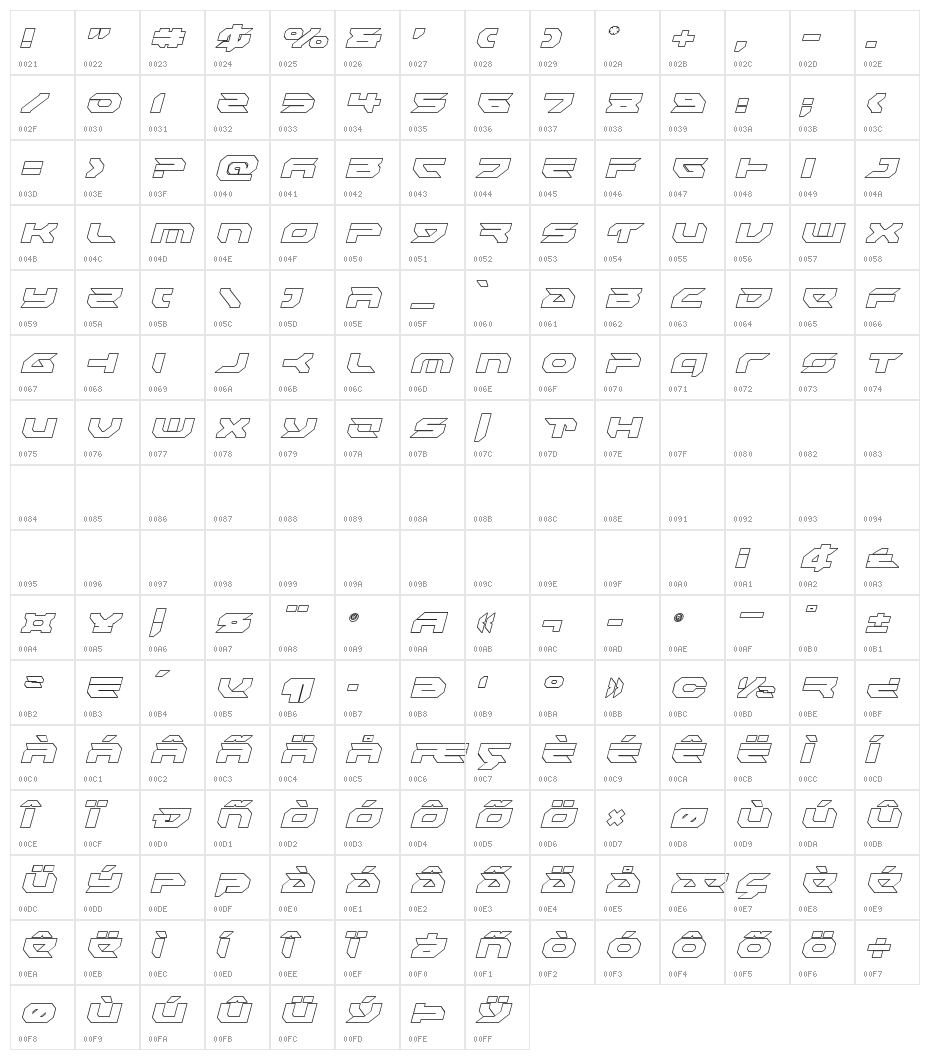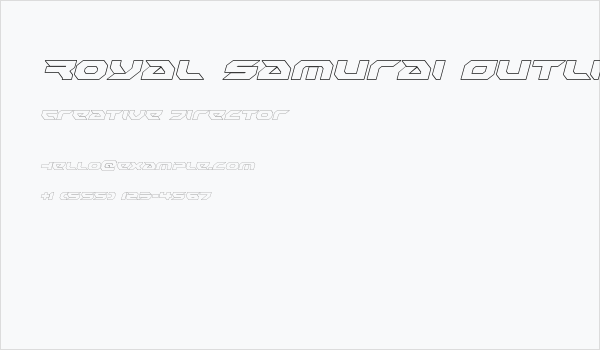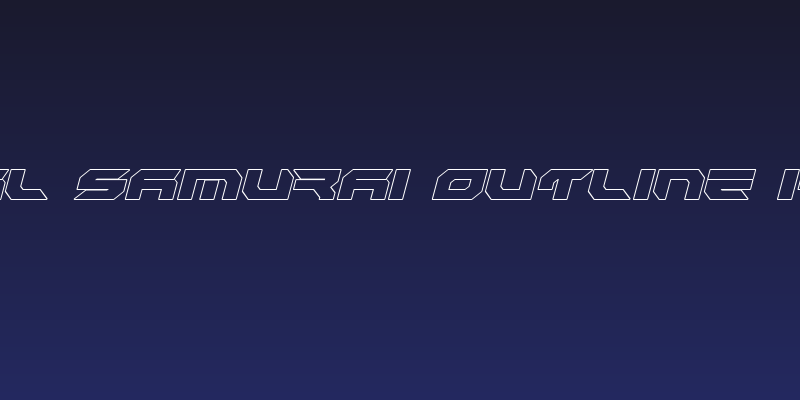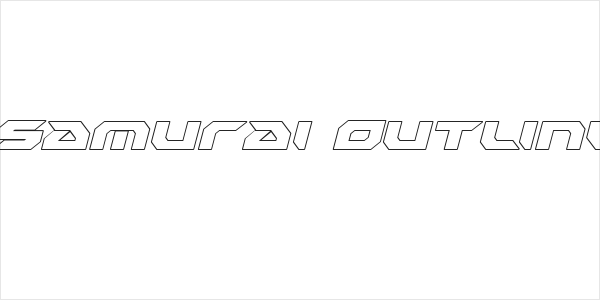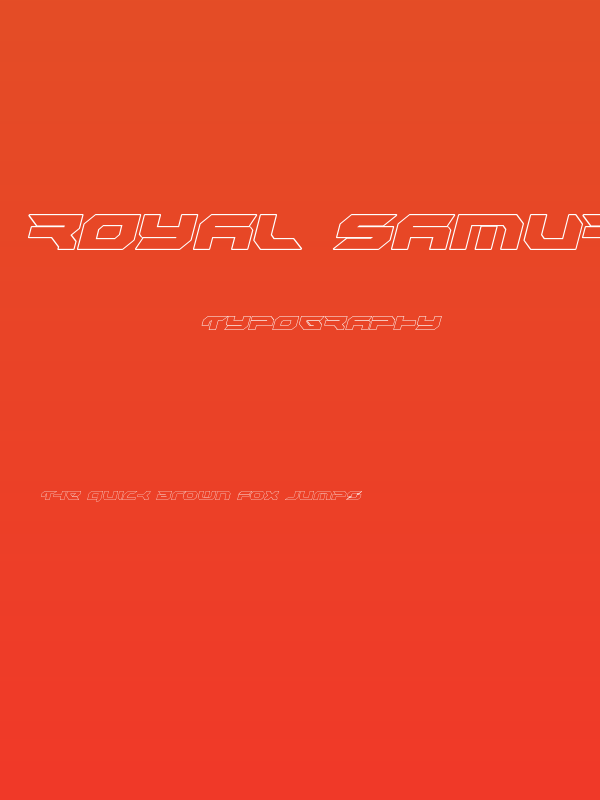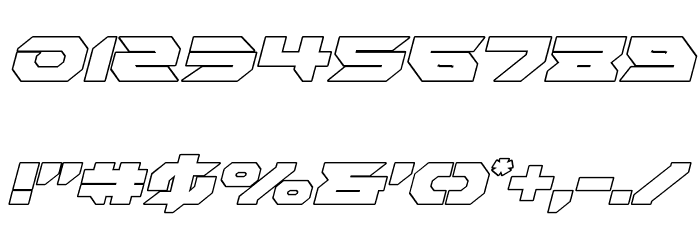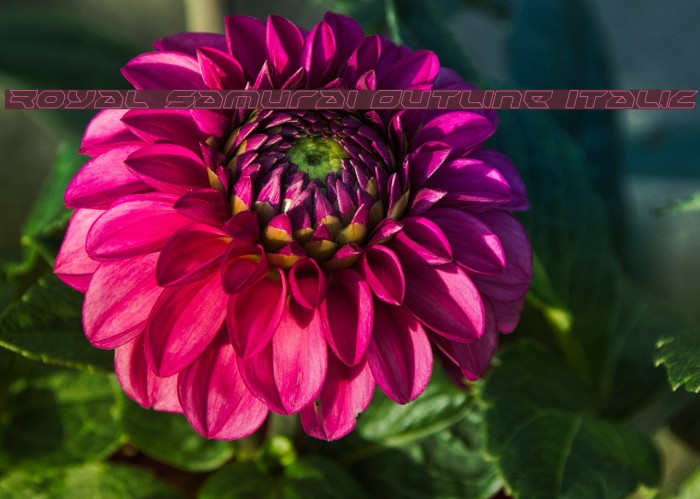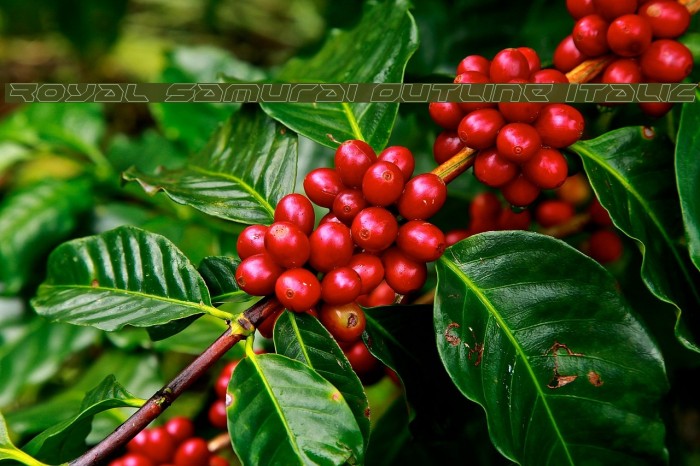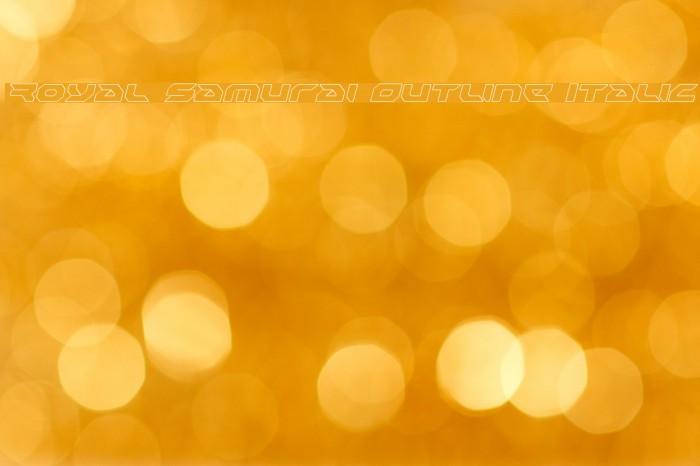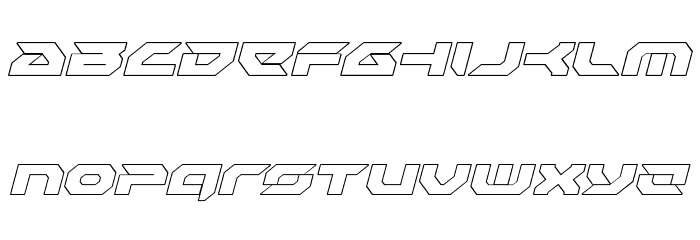
Royal Samurai Outline Italic Font
| Proyectos propuestos | Ideal for sci-fi themed designs, video game graphics, posters, and branding that requires a modern and edgy look. |